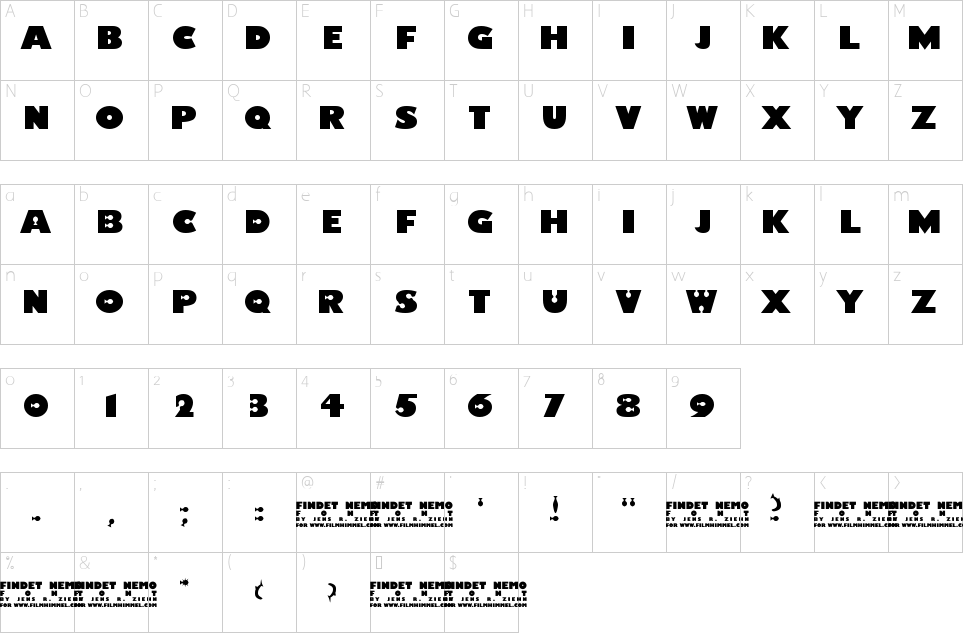
A fonte Findet Nemo é uma criação da Film Himmel – Jens R. Ziehn, disponível tanto para Windows quanto para Mac. Esta fonte, que é um verdadeiro hit entre os designers gráficos, já foi baixada mais de 254,000 vezes. Não apenas é uma opção incrível para projetos digitais, mas também para criações manuais. Suas linhas suaves e o design alegre e descontraído garantem uma experiência visual agradável. É perfeita para estilos de design infantil, animação e até mesmo letras de músicas. Se você está procurando por uma fonte que será tanto uma ferramenta versátil quanto uma escolha de estilo, Findet Nemo é uma ótima escolha.